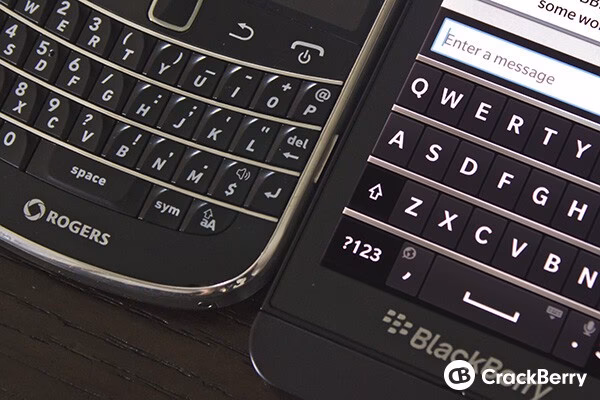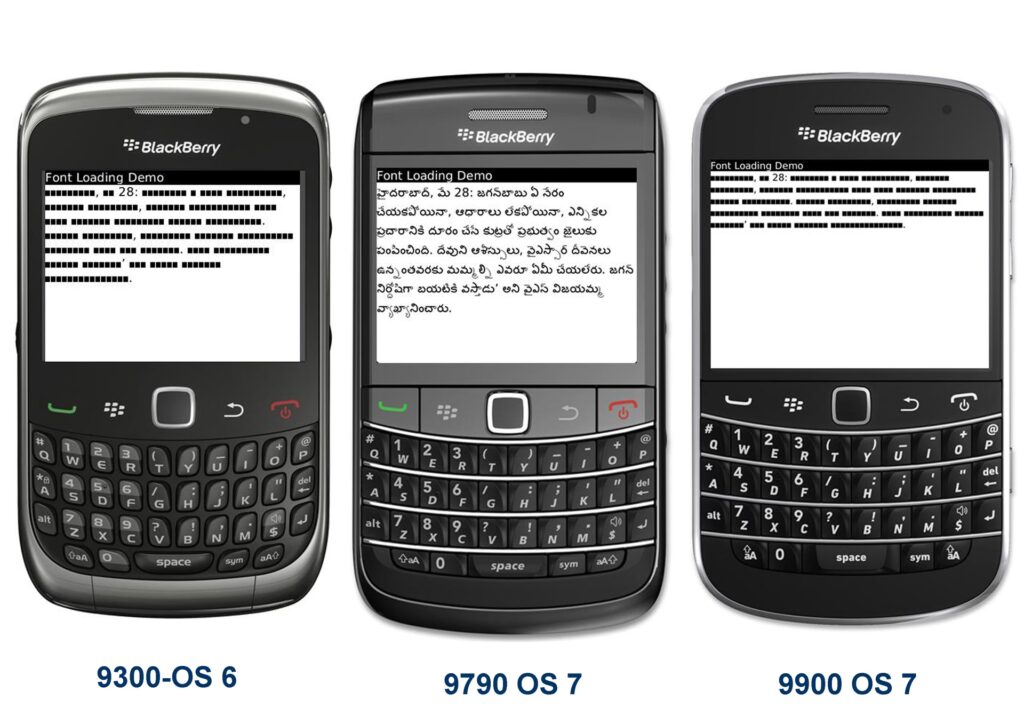
Udforsk BlackBerry Skrifttypen: Et Dyk Ned i Dens Verden
I en verden domineret af digitale medier og visuel kommunikation spiller skrifttyper en afgørende rolle i at forme vores oplevelser. Hver font bærer en unik personlighed, der kan påvirke alt fra læsbarhed til den overordnede æstetik i et design. Blandt de utallige skrifttyper, der er tilgængelige, skiller visse sig ud på grund af deres historie, deres æstetiske appel eller deres association med ikoniske brands. BlackBerry-skrifttypen er en af disse. Selvom den måske ikke er lige så udbredt som nogle af de mest populære systemskrifttyper, har den sin egen charme og anvendelse, især for dem, der har en forkærlighed for den klassiske BlackBerry-æstetik.
Hvad er BlackBerry Skrifttypen?
BlackBerry-skrifttypen, eller mere præcist den skrifttypefamilie, der er associeret med det engang så dominerende mobiltelefonmærke BlackBerry, repræsenterer en æra inden for mobilkommunikation. Selvom BlackBerry ikke længere har den samme markedsandel som tidligere, lever deres designæstetik videre, og skrifttypen er et centralt element i denne arv. Den er ofte karakteriseret ved en ren, læselig og let moderne stil, der afspejler mærkets fokus på produktivitet og effektivitet. Den oprindelige font, der blev brugt af BlackBerry, var designet til at være klar og funktionel på små skærme, hvilket var en nødvendighed i de tidlige dage af smartphone-teknologi.
Karakteristika ved BlackBerry Skrifttypen
BlackBerry-skrifttypen, i sin mest genkendelige form, udviser flere distinkte træk:
- Renhed og Klarhed: Fonten er designet med fokus på maksimal læsbarhed. Bogstaverne er veldefinerede, med god afstand mellem dem, hvilket sikrer, at teksten er let at læse, selv i mindre størrelser eller på skærme med lavere opløsning.
- Moderne, men Klassisk Æstetik: Den balancerer mellem et moderne, strømlinet udseende og en tidløs klassisk appel. Dette gør den alsidig og velegnet til en række forskellige anvendelser.
- Minimalistisk Design: Ofte uden unødvendige udsmykninger eller seriffer, hvilket bidrager til dens rene og professionelle udseende. Dette passer godt til den produktivitetsorienterede image, som BlackBerry engang havde.
- Tilpasningsevne: Fonten kan bruges i en bred vifte af sammenhænge, fra webdesign og applikationsgrænseflader til trykte materialer og branding.
Sammenligning med Andre Populære Skrifttyper
For at sætte BlackBerry-skrifttypen i perspektiv, lad os sammenligne den med et par andre populære og ofte brugte skrifttyper:
| Skrifttype | Primære Karakteristika | Typisk Anvendelse | Licens (Generelt) |
| BlackBerry | Ren, læselig, moderne, minimalistisk | Mobilgrænseflader, produktivitetstemaer, retro-design | Gratis til personlig og kommerciel brug (afhængig af kilde) |
| Roboto | Geometrisk, moderne, alsidig, meget læselig | Android OS, webdesign, applikationer | Gratis (Apache License 2.0) |
| Open Sans | Humanistisk sans-serif, venlig, læselig | Webdesign, branding, brugergrænseflader | Gratis (Open Font License) |
| Helvetica | Klassisk, ren, neutral, alsidig | Branding, typografi, printdesign | Kommerciel licens påkrævet |
Sammenlignet med skrifttyper som Roboto og Open Sans, deler BlackBerry-skrifttypen en vis grad af renhed og læsbarhed. Dog har den en unik nostalgisk appel, der er knyttet til BlackBerry-brandet, hvilket giver den en særlig plads for dem, der søger denne specifikke æstetik. I modsætning til Helvetica, som kræver en kommerciel licens, er BlackBerry-fonten, som gjort tilgængelig af Ivan Lisichkin, et attraktivt alternativ for budgetbevidste designere.
Når du bruger BlackBerry-skrifttypen i dine projekter, er her et par tips til at maksimere dens potentiale:
- Kombiner med Komplementære Skrifttyper: Selvom BlackBerry-fonten er alsidig, kan den se endnu bedre ud, når den kombineres med en anden skrifttype, f.eks. en serif-font til brødtekst, for at skabe kontrast og visuel interesse.
- Brug til Branding: Hvis du arbejder med et projekt, der har en retro-teknologi-vibe eller ønsker at fremkalde en følelse af produktivitet og klassisk mobilkommunikation, er BlackBerry-fonten et oplagt valg.